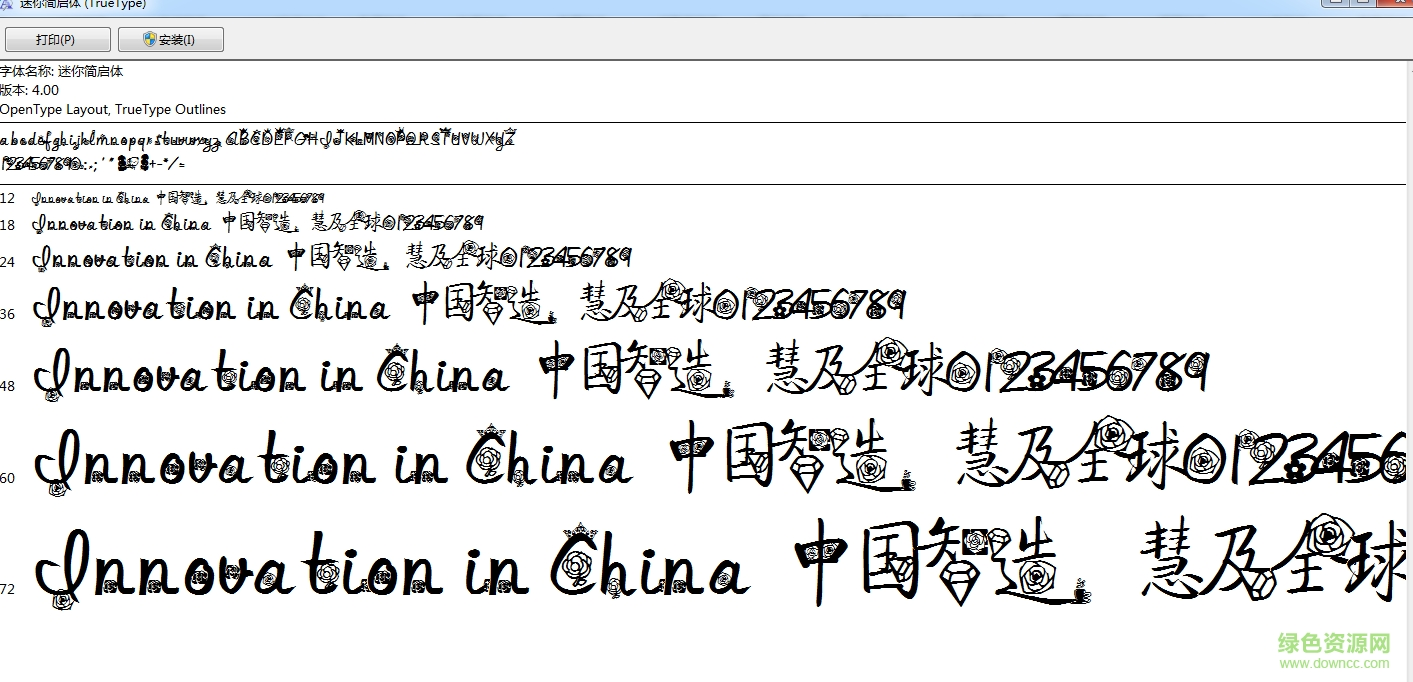
玫瑰鉆戒愛(ài)情字體是一款粗細(xì)勻稱的個(gè)性字體,清新優(yōu)雅,實(shí)用性與美觀性兼?zhèn)?,好似?ài)情甜甜蜜蜜,廣泛應(yīng)用于廣告設(shè)計(jì)、宣傳海報(bào)、ppt、影視制作等領(lǐng)域!有需要者趕緊來(lái)綠色資源網(wǎng)下載吧!
玫瑰鉆戒愛(ài)情字體字型飽滿,間隔均衡,加鋒較小,整體美觀而不落俗套!